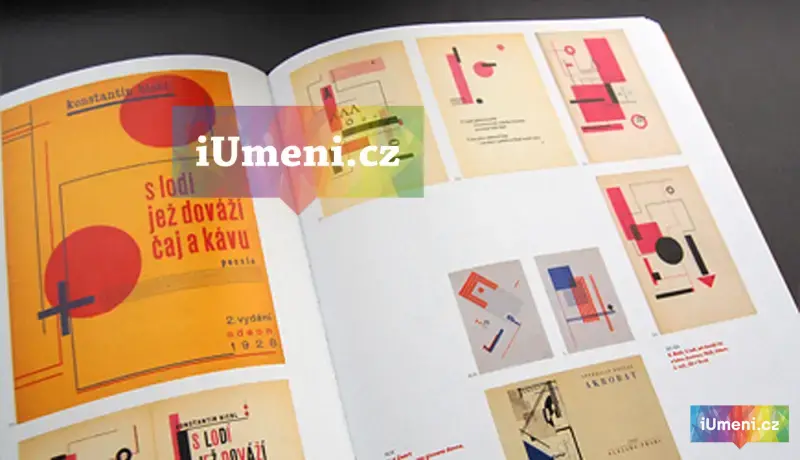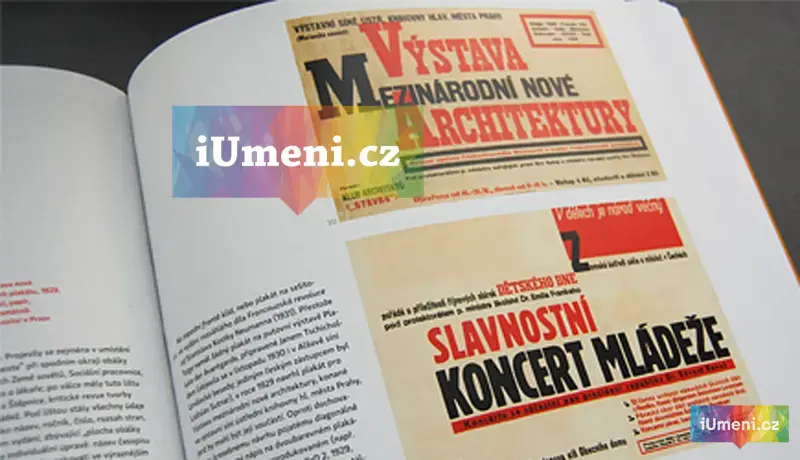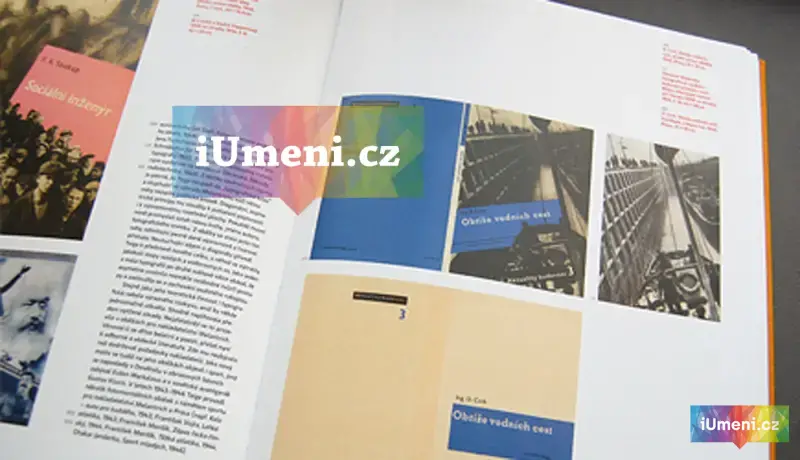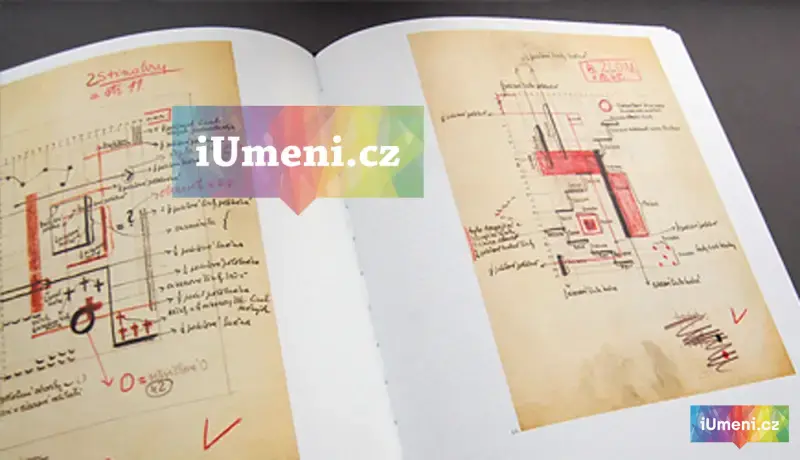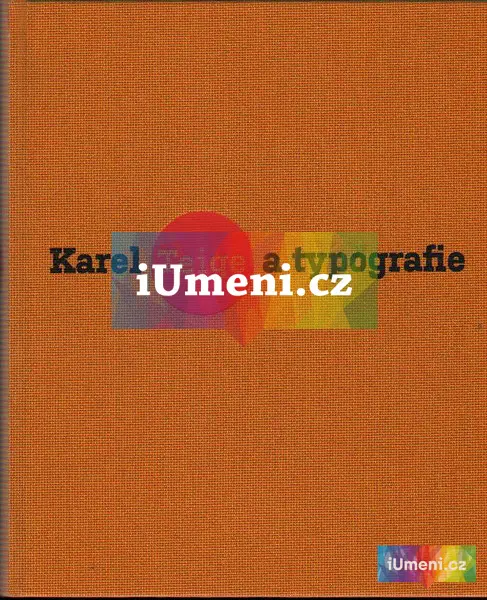
Karel Teige a typografie
KataMonografie Karel Teige a typografie je populárně vědecká práce popisující období více než třiceti let ve vývoji české typografie. Její význam tkví především v tom, že nabízí souborný pohled: podává ucelený a zasvěcený obraz typografického díla jedné z nejvýraznějších českých osobností tohoto oboru..
Karel Teige (1900–1951) je znám zejména jako teoretik výtvarného umění a architektury, publicista, kritik, redaktor a organizátor českého uměleckého života století. Stal se vůdčí osobností avantgardního uměleckého sdružení Devětsil (1920) a od roku 1934 i pražské surrealistické skupiny. Byl také autorem koláží, dosud však unikala pozornosti neméně podstatná část jeho umělecké tvorby – knižní úprava a typografie. Teige patřil nejen k teoretickým průkopníkům nové typografie, ale sám byl po téměř třicet let činný jako aktivní typograf, který upravil množství knih, časopisů, plakátů, dopisních papírů a akcidenčních tisků. Zasloužil se o neopakovatelnou podobu mnohých významných básnických sbírek Františka Halase, Vítězslava Nezvala či Jaroslava Seiferta, spolupodílel se na typografické úpravě nejdůležitějších dobových sborníků a časopisů (Devětsil, Život 2, ReD), úzce spolupracoval s předními nakladatelstvími (Odeon, Aventinum, Fr. Borový). Zvláštní pozornost si zaslouží zejména jeho technika propojení knižní obálky a koláže. Teigův obsáhlý typografický výkon, zahrnující několik set položek, vytváří základní vklad do evropské meziválečné a krátkodobě i poválečné knižní kultury. Již ve své době byl Karel Teige uznávanou a oceňovanou osobností, která své typografické dílo prezentovala po celém světě. První česká monografie věnovaná sumarizaci Teigova typografického díla se díky komparativnímu a konfrontačnímu zřeteli současně stává uceleným přehledem dějin moderní tuzemské knižní tvorby. Kniha je vybavena mimořádně bohatým obrazovým doprovodem, obsahuje navíc také výběr z vlastních teoretických textů Karla Teigeho věnovaných typografii a objevný soupis jeho typografického díla. Je uzavřena podrobným německým a anglickým resumé.
„Klady: Reprezentativní publikace.“